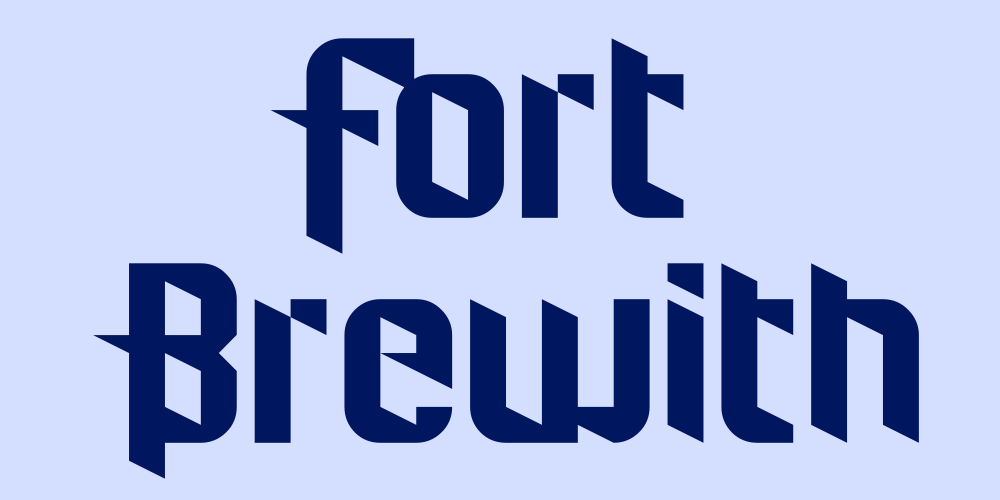
A Fort Brewith é uma elegante fonte do tipo Blackletter que captura o encanto nostálgico das antigas impressões manuscritas. Seu design cuidadosamente criado por Hamilton, transmite um sentimento rico de história e tradicionalismo, perfeitamente adaptável para aplicações como letras góticas em cartões de aniversário, nomes religiosos ou até mesmo em texturas vintage de websites. Com seu estilo único que se destaca em qualquer ambiente gráfico, a Fort Brewith é uma escolha inteligente para quem deseja dar um toque especial ao seu design digital.